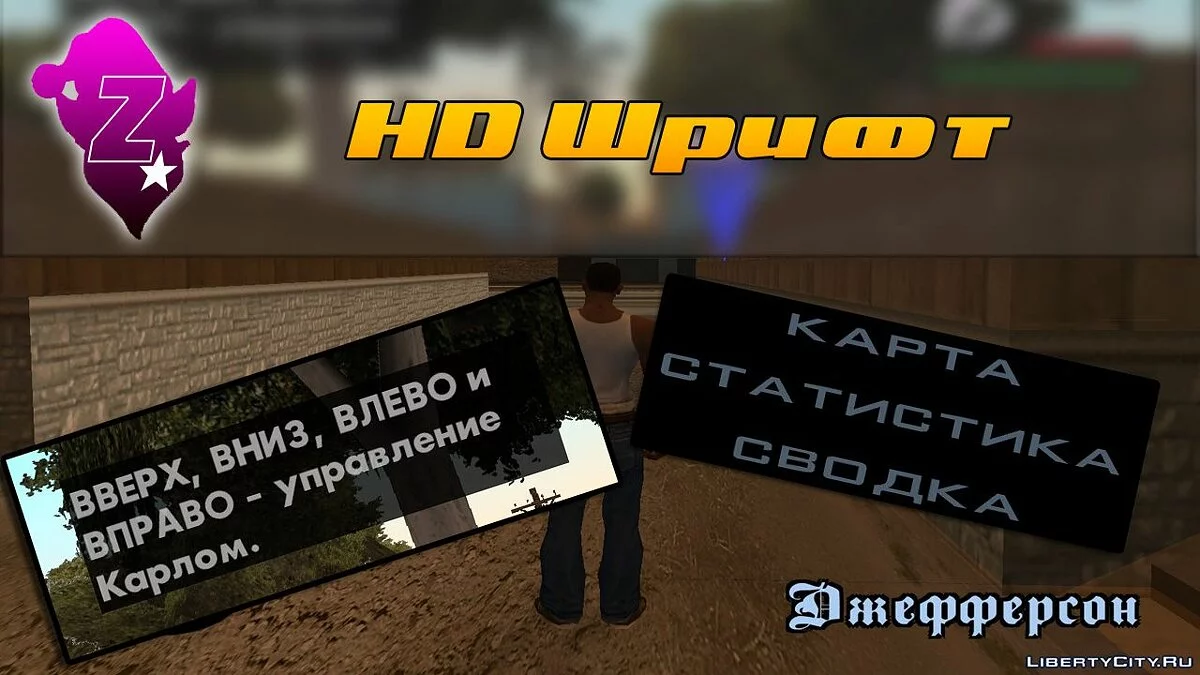
HD fonts
Русские HD шрифты из "GTA VC Возвращение", понятно в гламурном стиле. Подходят для большинства русификаторов. Текстуры имеют размер 4096x4096 (!).